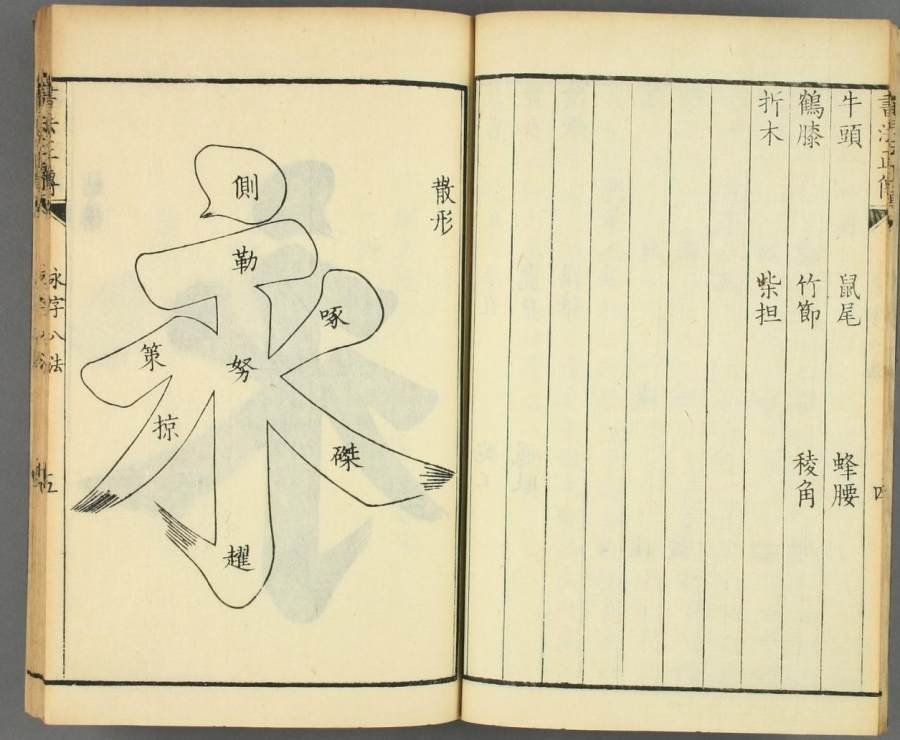
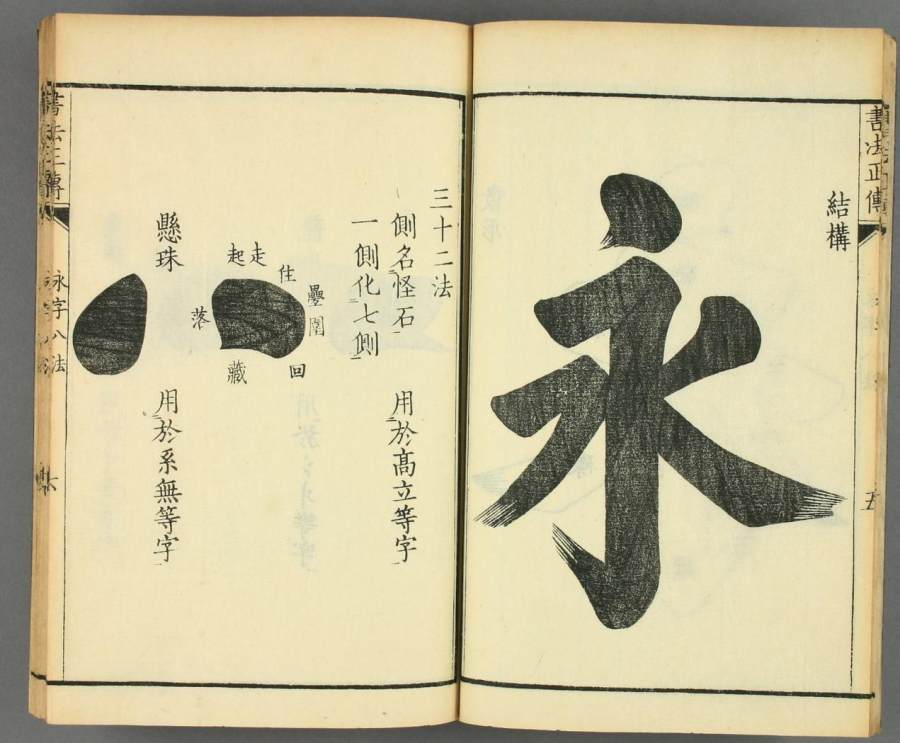
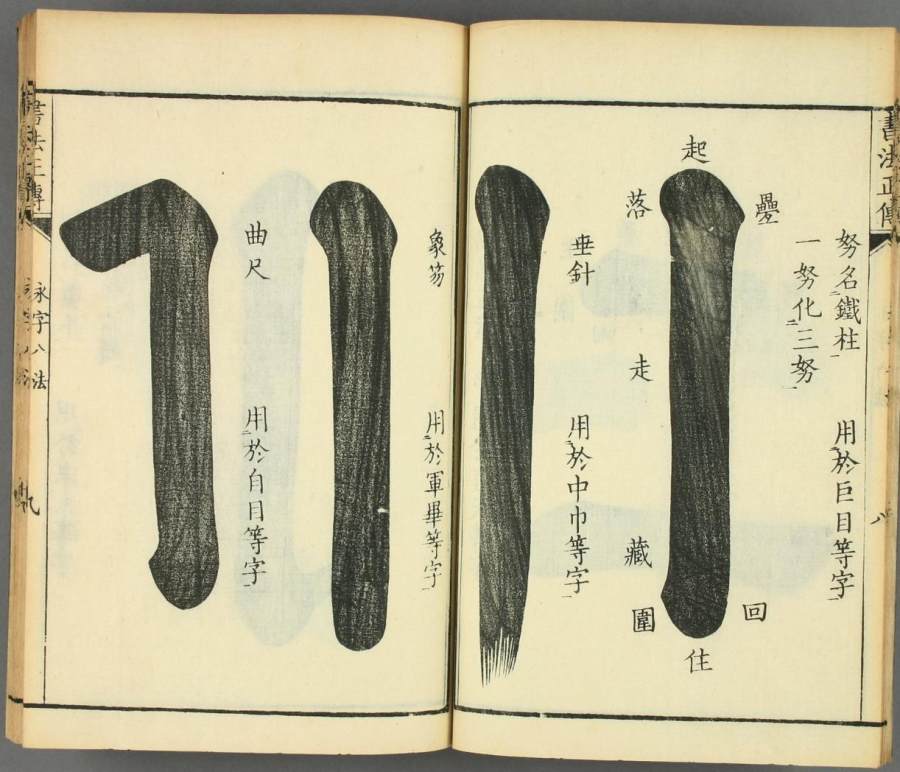
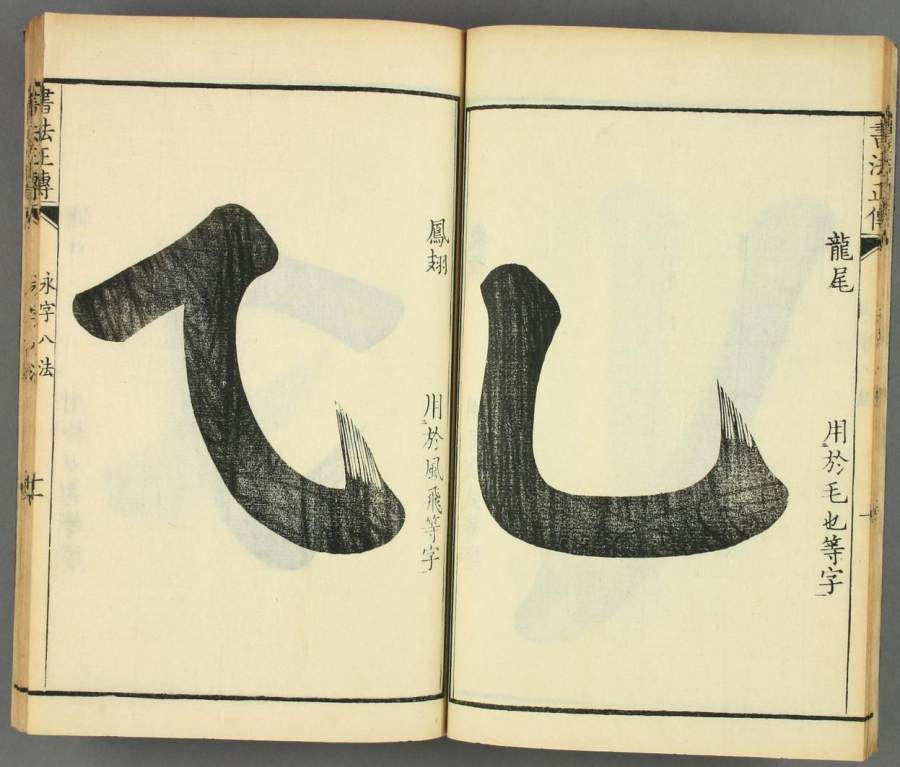
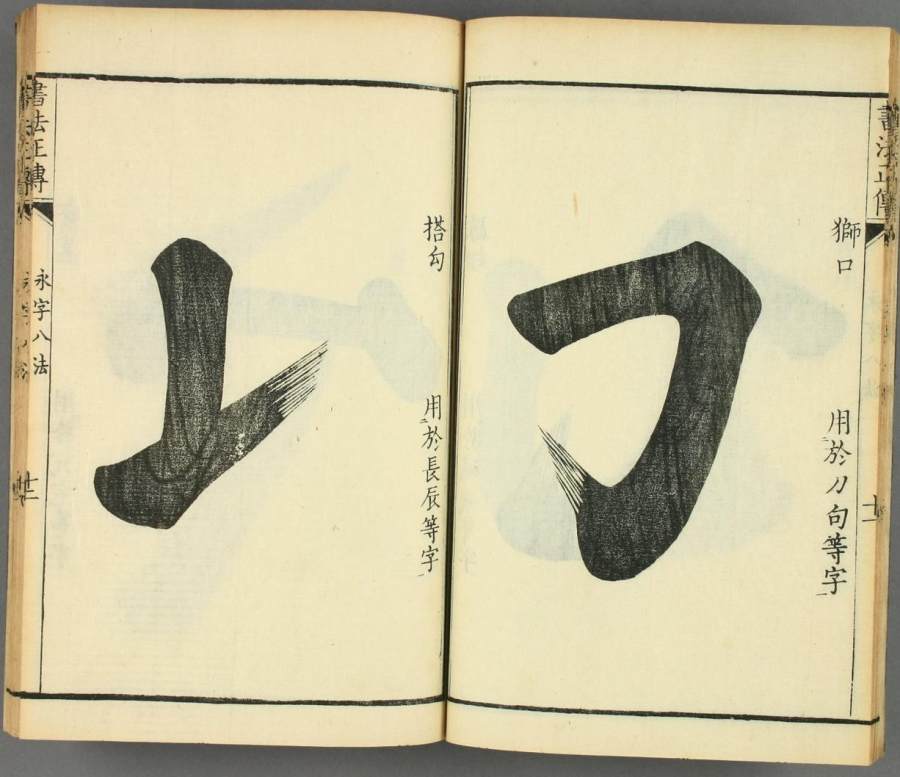
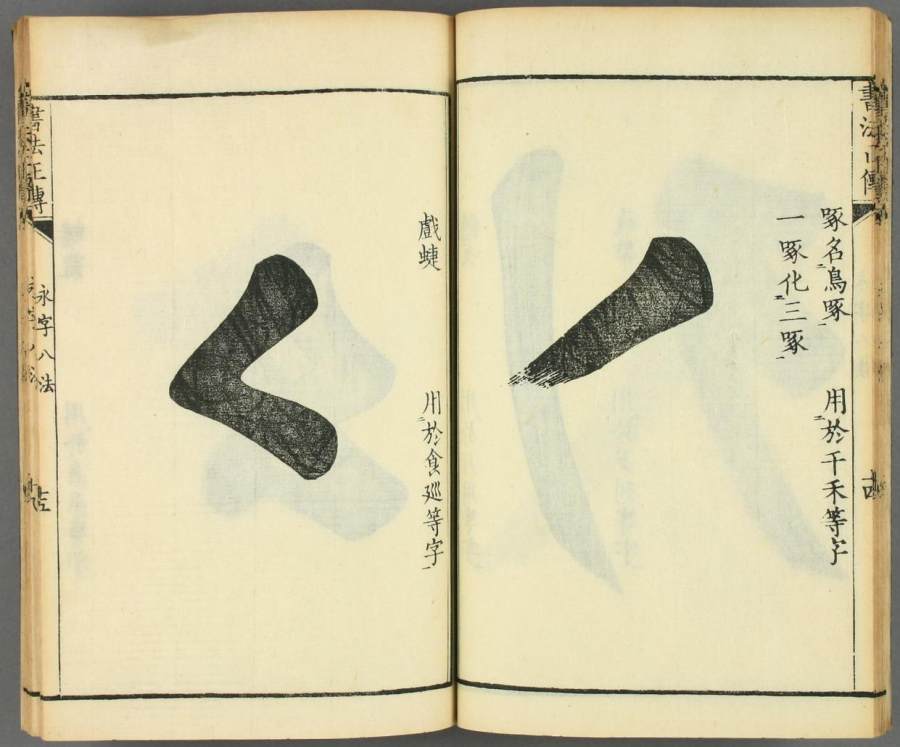
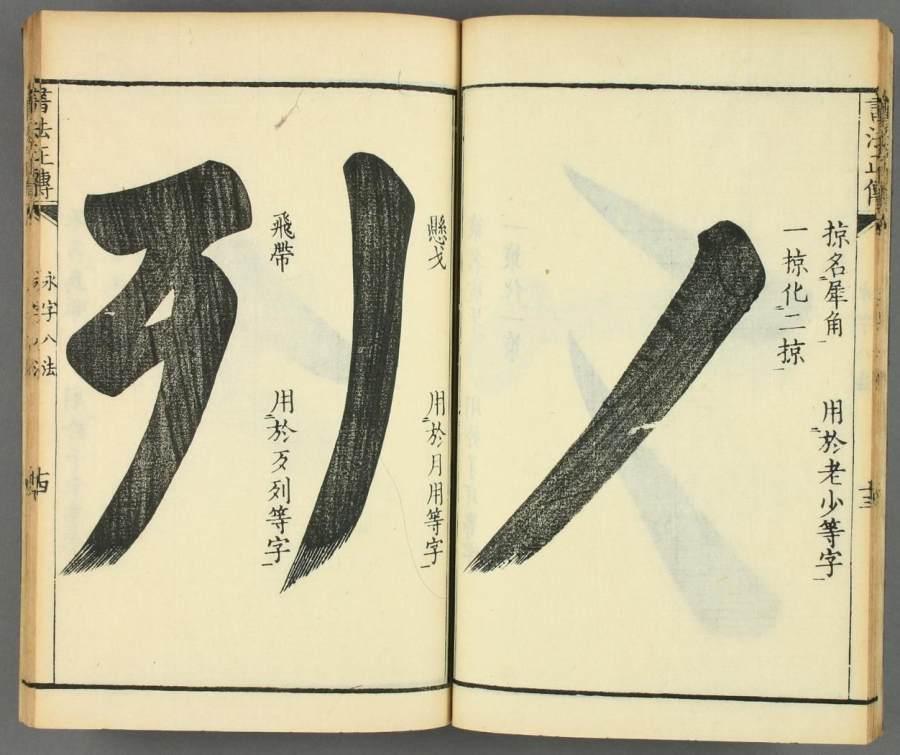
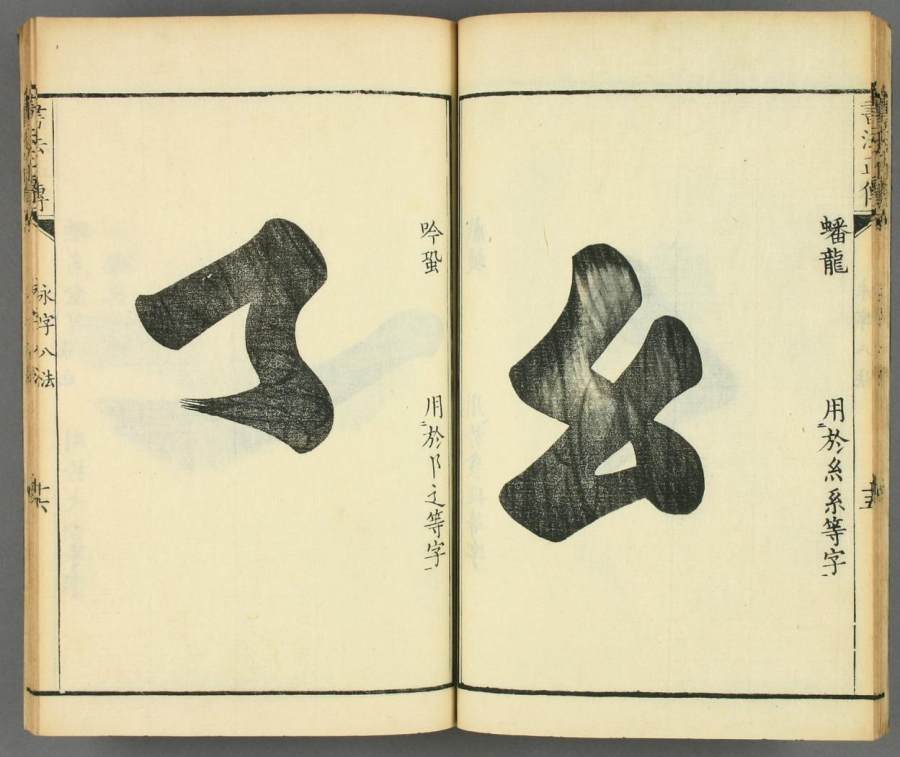
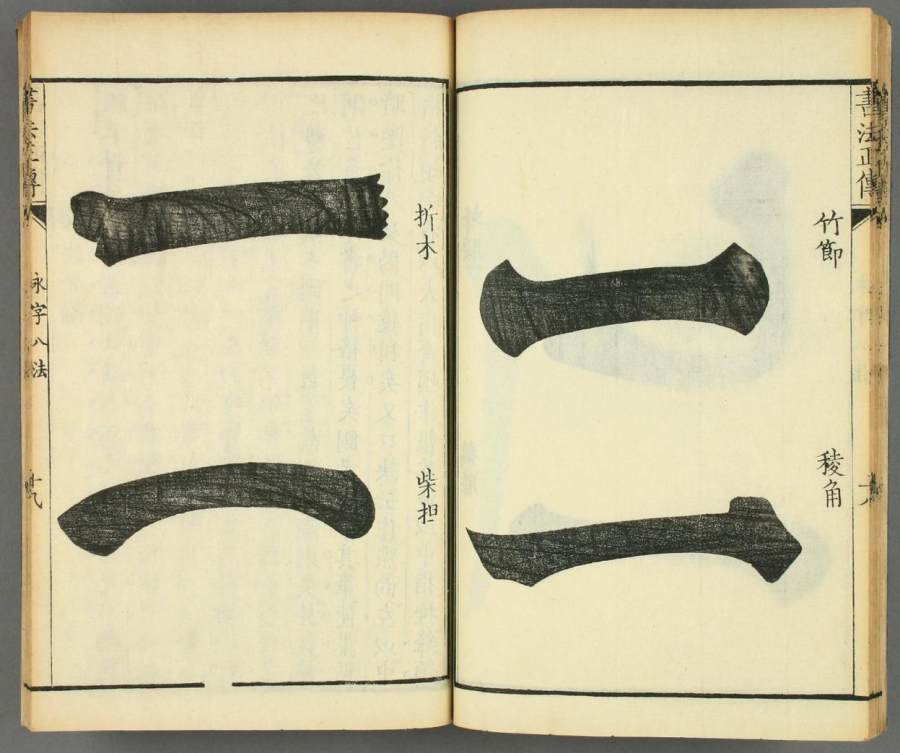
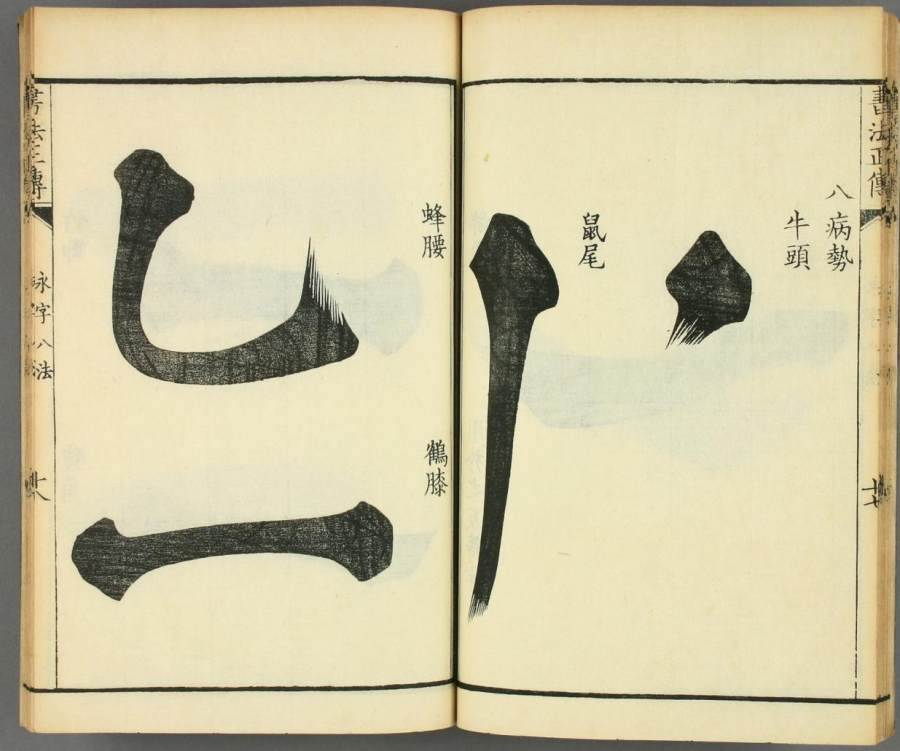
《书法正传》是清冯武编的一套比较完备的楷书技法理论集刊。卷一至四为技法部分,包括:翰林要诀、书法三味、字体之永字八法、大字结构八十四法;卷五到七为纂言及汉至元人论书,卷八九为:书家小传、名迹源流;卷十为钝吟书要,此本为和刊本。
书前“自序”是以答缪子之间的形式而展开的,主要介绍作者的书学宗旨。叙述书体的发展过程,称“古文而为篆籀,篆籀变而为分、小篆,小篆变而为隶兼篆,隶变而为今正书,正书变而为行书、章草,章草变而为草书,诸体之中惟正书最为切要焉”。继以“凡例”分条而具体说明编纂之旨,如选录书论之意在“书家之书,所引用者最苦于不肯全载。余读虞永兴《笔髓》、孙过庭《书谱》……诸书,皆字字珠玉,资助后学不浅,故全录不遗”。选录名家依据在“古今书家不知凡几,不能全载,特取尤当熟悉者”。选录书迹依据在“晋唐名迹所无几,后代翻刻,不可胜计。拟核其真赝,溯其存亡……以便稽考也”。其编著之旨为“非紧要者一语不载,所关切者宁屡见焉”。本编虽为辑录,但时参己见。
卷一所载《翰林要诀》,元陈绎曾撰。陈绎曾(生卒年不详),字伯敏,处州(今浙江丽水)人。共分十二日:一、“执法”,介绍指法、腕法、手法等;二、“血法”,介绍“蹲、驻、提、捺、过、抢、衄”等;三、“骨法”,介绍“提、纵”等;四、“筋法”,介绍“字法”中的“藏、度”等;五、“肉法”,介绍“满捺”与“飞 ,提”,并附“笔、纸、墨、砚”等;六、“平法”,分述“偃、仰、平、勒”等;七、“直法”,分述“垂露、悬针、向、背、努、僵”等;八、“圆法”,分述“点、撇、捺、策、趣、勾、方”等;九、“方法”,分述“八面、九宫、结构、均方”等;十、“分布”,分述“布方、映带、变换、体样、字间、行白、篇段”等;十一、“变法”,分述书法的“情、气、形、势”等;十二、“法书”,介绍“真书”五十四种,“行书”十二种,“草书”三种,并列“法帖”二十四部等。
卷二所载《书法三昧》,元周伯琦撰。周伯琦(1298—1369年),字伯温,号玉雪坡真逸,饶州(今江西波阳)人。作品首录“书法题辞”,即《书法三昧歌》,以四言古韵阐述“执笔”、“运笔”之法。继为“下笔”、“布置”和“运用”等三则,分别介绍书学“三昧”之法。再列书法“结构”,如“云空、九见、门月、来东……”等五十四类,一一分条列目而叙之。末附《衍极》“至朴”篇的“书法流传”部分,上始蔡邕、下至柳宗元,“直捷精至,览之使人洞然无疑”。
卷三所载《永字八法》,元李溥光撰。李溥光(生卒年不详),字玄晖,号雪庵,大同(今属山西)人。作品共有十一目:八法 历解,把笔八法,运笔八法,永字八法,八病,永字散形,三十二势,八病势,八法分论,颜鲁公《八法颂》,柳宗元《八法颂》。作者从“把笔、运笔、形势、结构、得失”等多种角度论述了“永字八法”之原理,并附录颜鲁公与柳宗元两家的《八法颂》。
卷四所载《大字结体八十四法》,明李淳撰。李淳(生卒年不详),号憩庵,茶陵(今属湖南)人。作品取陈绎曾、徐庆祥两家之作,对用笔之法、结构之道详加辨析,以求其蕴奥。原有“天覆、地载、分疆”等,总而辑之,共一百十三目。去其紊乱,选五十八目。续添“二段、三停、捺”等二十六目,合前共八十四目。每条取四字为例,各作一论,以开字法之奥。此法较欧阳《三十六法》更为具体,实为研习大字之楷模。
卷五、六、七分别载《纂言》上、中、下三卷,共收录自秦代李斯《用笔法》、汉代萧何《笔法》和蔡邕的《书说》,至明代丰道生《书诀》等著名的书学论著六十八篇,篇末各加补注。
卷八《书家小传》介绍秦、汉至元、明等十三代共七十二名书家之简历,并附“书家品藻”,内录朱长文《论品藻》、庾肩吾《书品》等名著十篇,及《杂识》一篇。
卷九《名迹源流》则收列锺繇《贺捷表》、《宣示表》等晋唐名帖共三十五部,每帖之后均附作者的短评,核其真赝,溯其存亡,各树见地。
卷十所载《钝吟书要》,清冯班撰。冯班《1602—1671》,字定远,号钝吟老人,江苏常熟人。作品以个人临池心得杂论学书之法,重在阐述“执笔”与“结字”,指出“晋人用理,唐人用法,宋人用意”。评论历代名家之长短,推崇晋唐之锺、王和颜、柳,以及宋元之蔡、赵。认为“不习二王,下笔便错”,“虞世南《庙堂碑》全是王法,最可师”。颜书“如正人君子,冠佩而立,望之俨然,即之也温”,“宋人蔡君谟书最佳,今人不重,只缘不学古尔”。深入揭示了晋理、唐法、宋意的书法规律,均各具创见,迥不犹人,可与宋曹的《书法约言》合称“双壁”,对学书与鉴赏都颇有启迪,故殿为《正传》之末。
冯武(1627—?),字窦伯,号缘。江苏常熟人。冯班从子。班以书法名当世,武受其学,亦能书、诗。以八十一高龄延馆苏州缪曰芑家树滋堂。在缪支持下,将所聚的数十种书学著作,披沙简金,辑成此书。